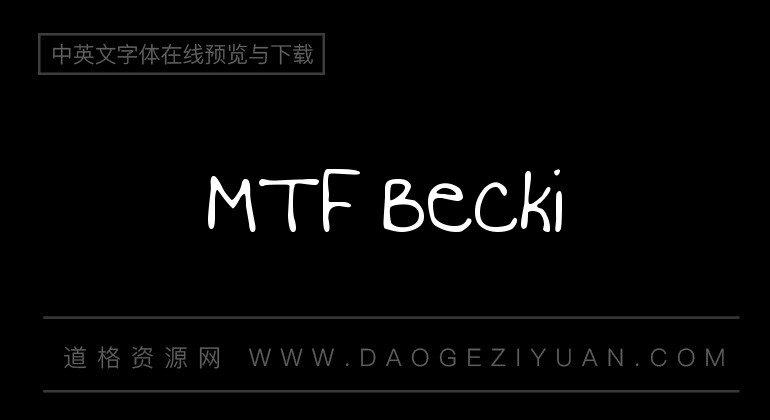
MTF Becki 是一种免费的手写风格字体。它由 MyTypoFactory 设计并发布,可以在个人和商业项目中免费使用。 该字体的风格像是在一个便签上手写的,非常适合用于标签、卡片、海报等项目中。它具有高度的可读性和清晰度,即使在小尺寸时也能保持清晰的轮廓。此外,该字体还包含了大写字母、小写字母、数字和标点符号,让您在设计项目中更加方便。 MTF Becki 字体可以在 MyTypoFactory 的网站上免费下载,支持 TTF 和 OTF 格式。如果您正在寻找一种免费的手写风格字体,那么 MTF Becki 可能会成为您的不错选择。内容介绍
MTF Becki是一款非常不错的手写艺术字体,具有很好的视觉感,适合于文化类的宣传设计、商业类品牌的广告和产品包装设计以及个性化文字排版等较多场景。